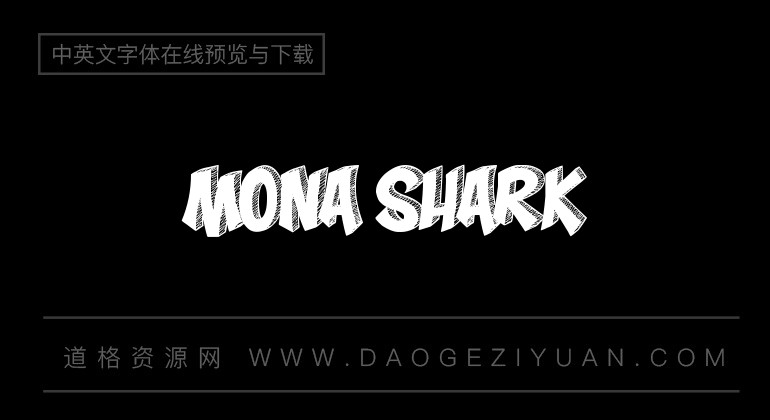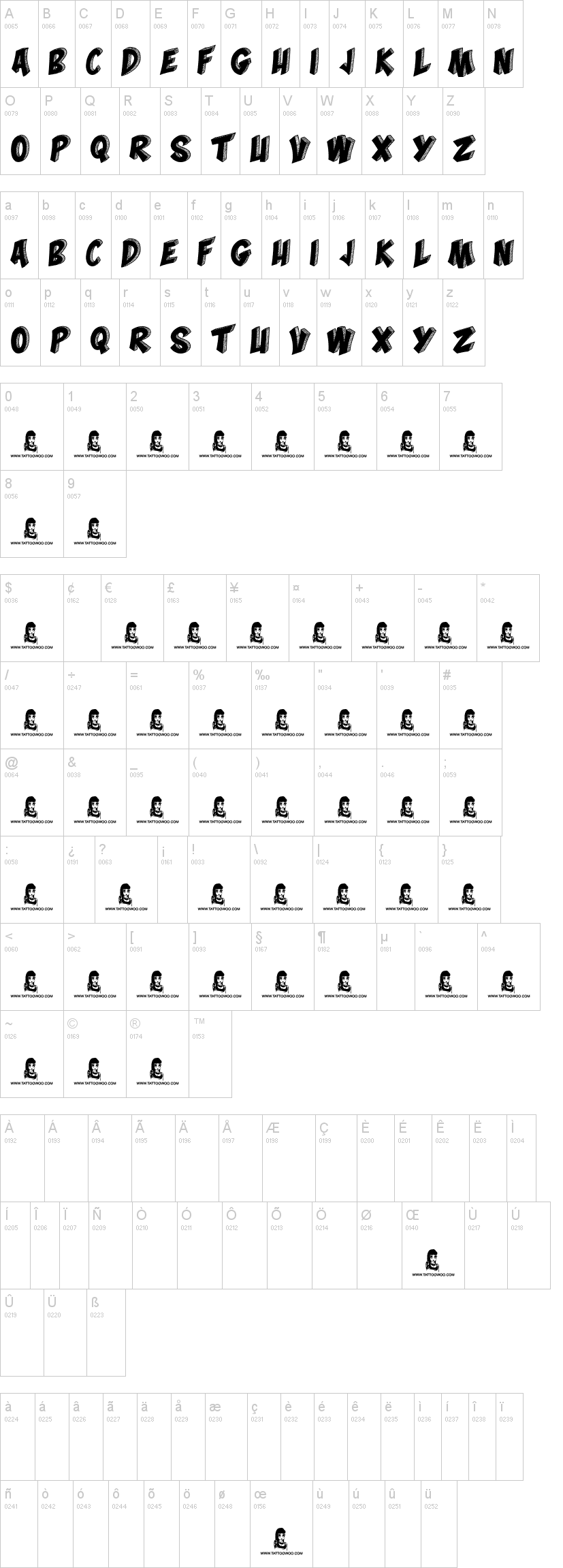
Mona Shark
? Mona Shark 字体是一款日本设计师Kyoichi Tsutaya设计的一款英文字体,它以海洋生物“鲨鱼”的形状作为灵感,结合了欧洲的古典字体风格,形成一种独特的字体风格,被广泛应用于品牌标识、商标、包装和海报等设计领域。Mona Shark字体的特点是:字体的线条粗细比较均匀,字体的曲线笔画自然,字体的结构比较紧凑,具有良好的可读性,可以让设计师在设计中获得良好的表现效果。
Mona Shark是一款非常不错的手写艺术字体,具有很好的视觉感,适合于文化类的宣传设计、商业类品牌的广告和产品包装设计以及个性化文字排版等较多场景。